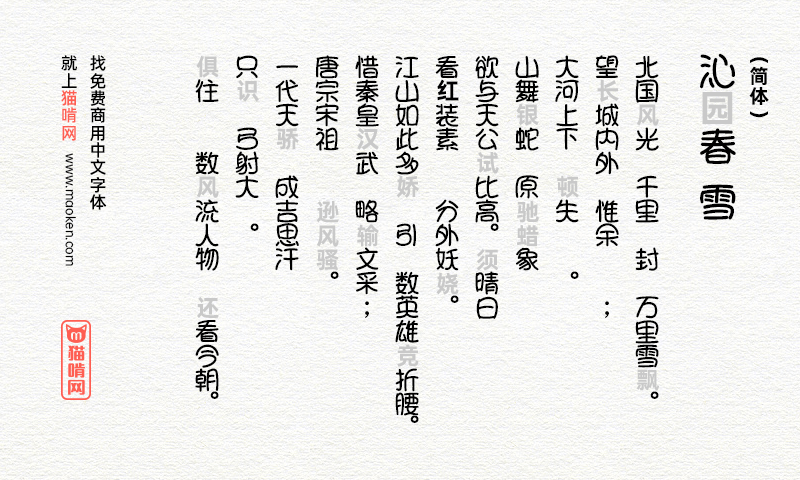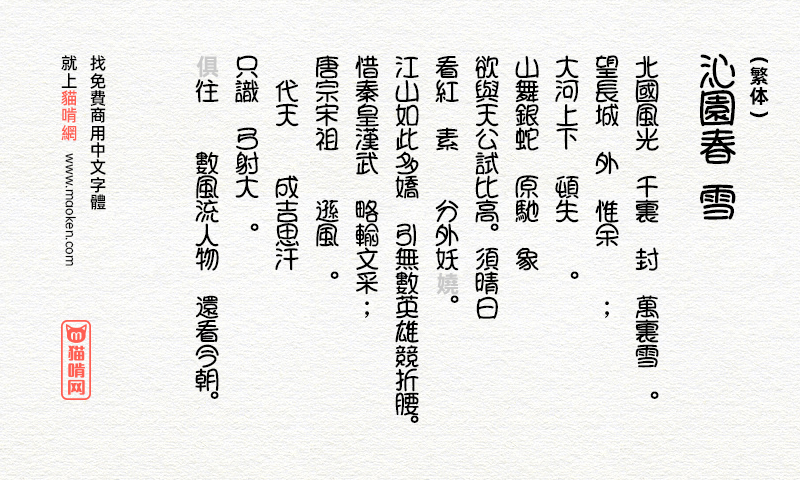
可爱少女体:散发着少女的魅力的可爱字型
字体作者:もじワク研究 (其他语种) 字体字重:1个
字体名称:可爱少女体(日文名:ポプらむ☆キュート )PS中字体名称: ポプらむ☆キュート
字体版本: Version 1.00 2017.03.12 收录汉字:简体★★ / 繁体★★★
这是一款来自日本的非常可爱的字体, 「 可爱少女体 」(日文名:ポプらむ☆キュート ) 。支持的汉字不算特别多,这是比较可惜的。但是其可爱的字型还是让人爱不惜手,喜欢这套字体的朋友们可以一试哦。说不定刚好有你想要的字体呢。
「 可爱少女体 」 收录汉字约3200个 (JIS第1水准2965字,第2水准260字)
字都不能显示